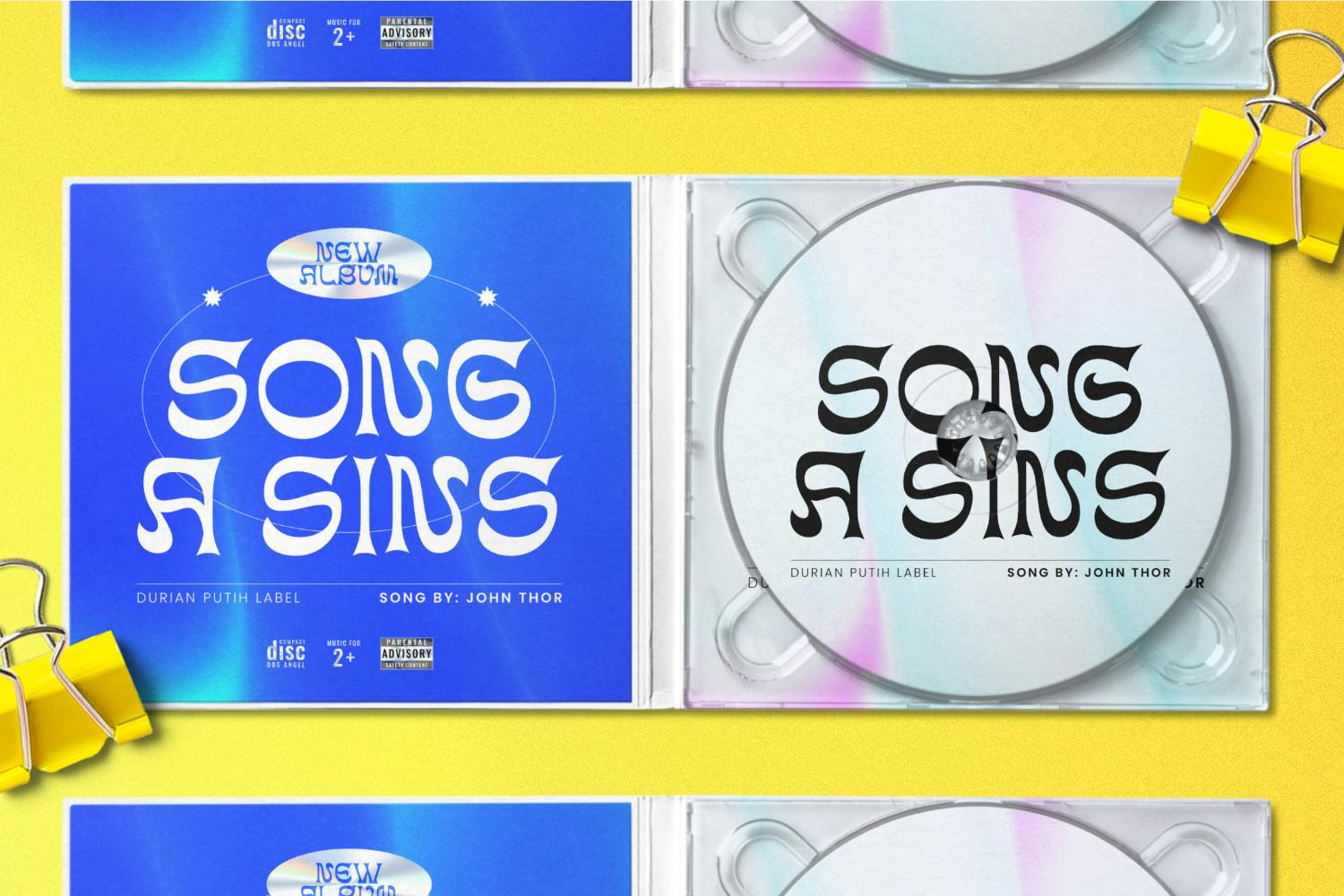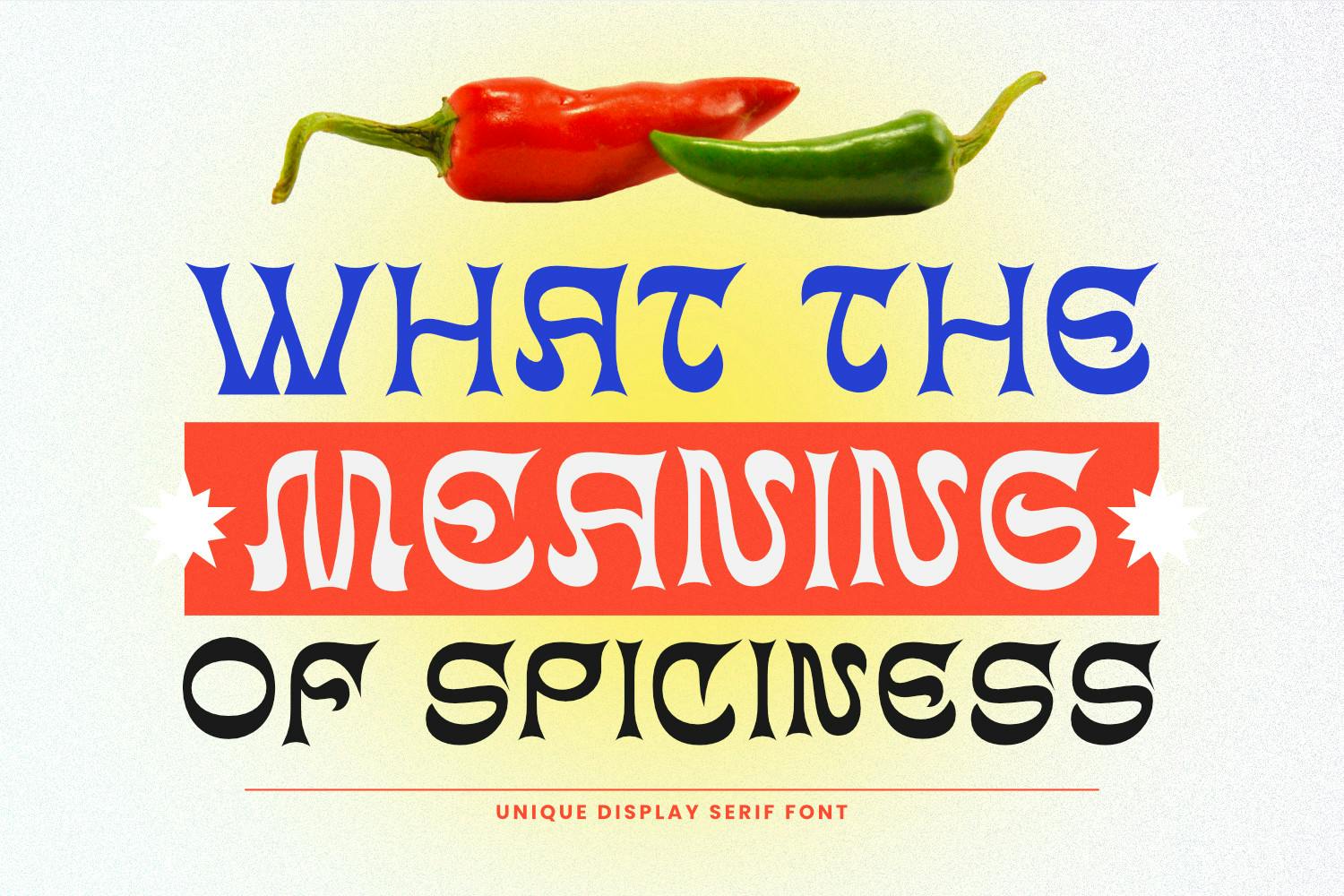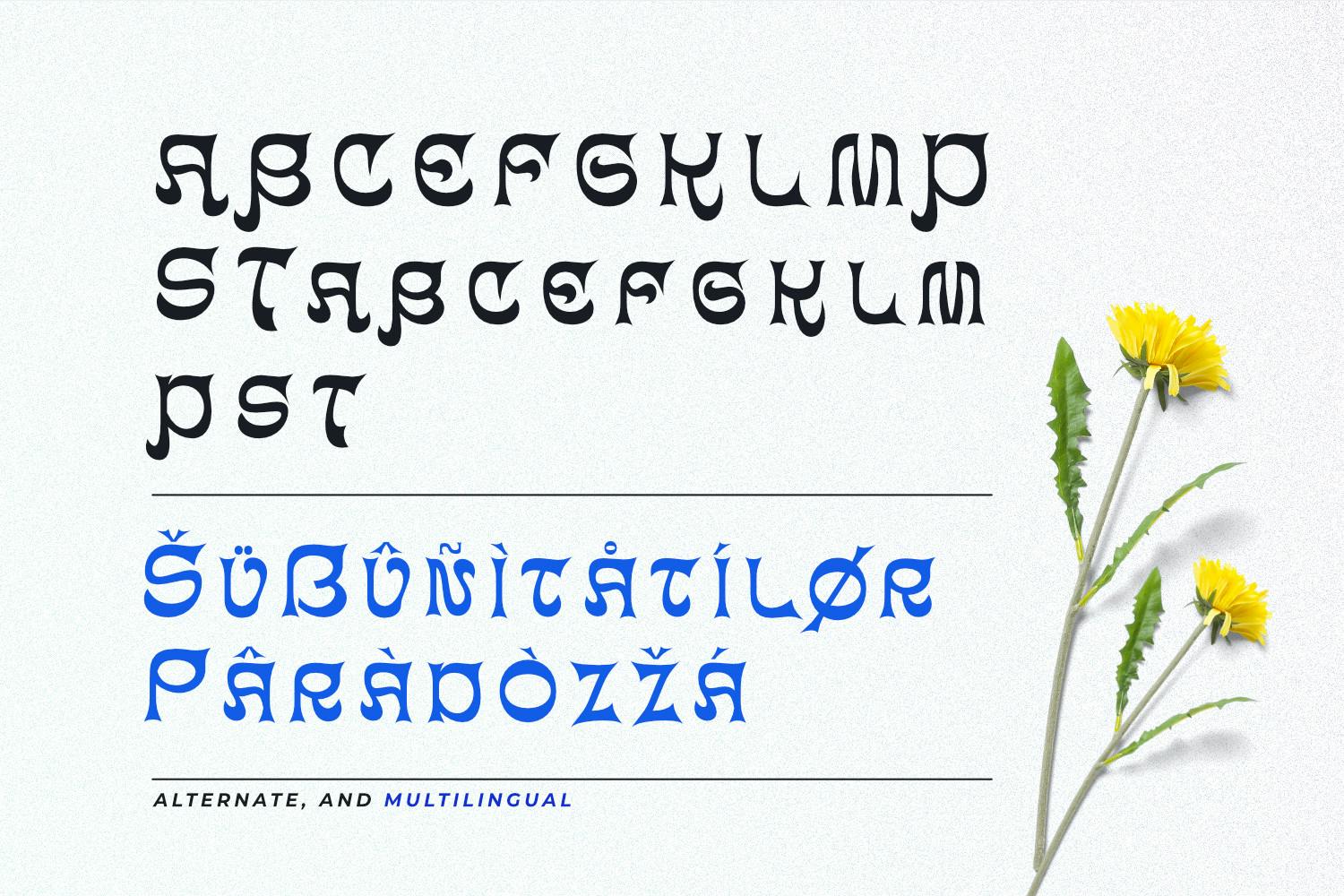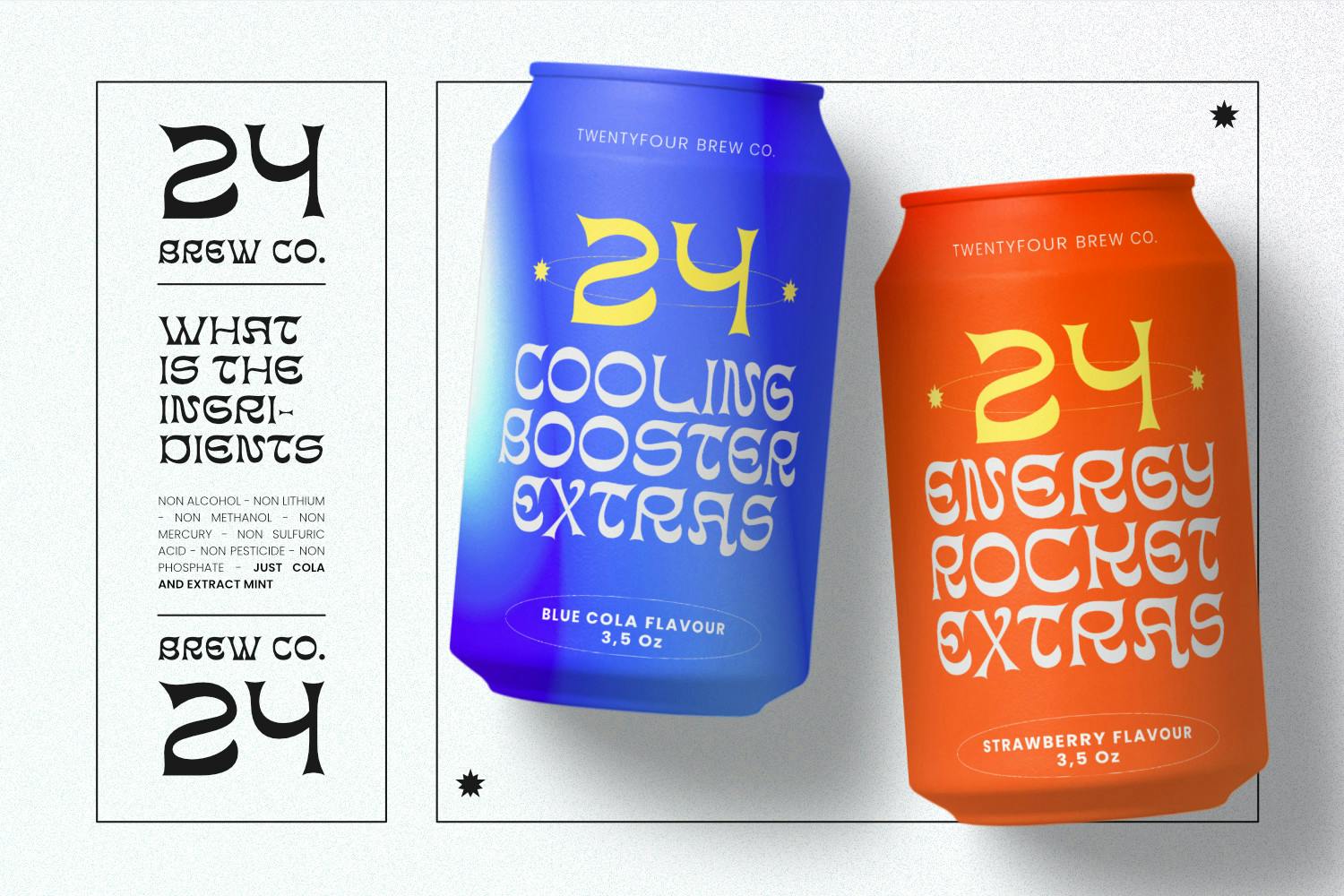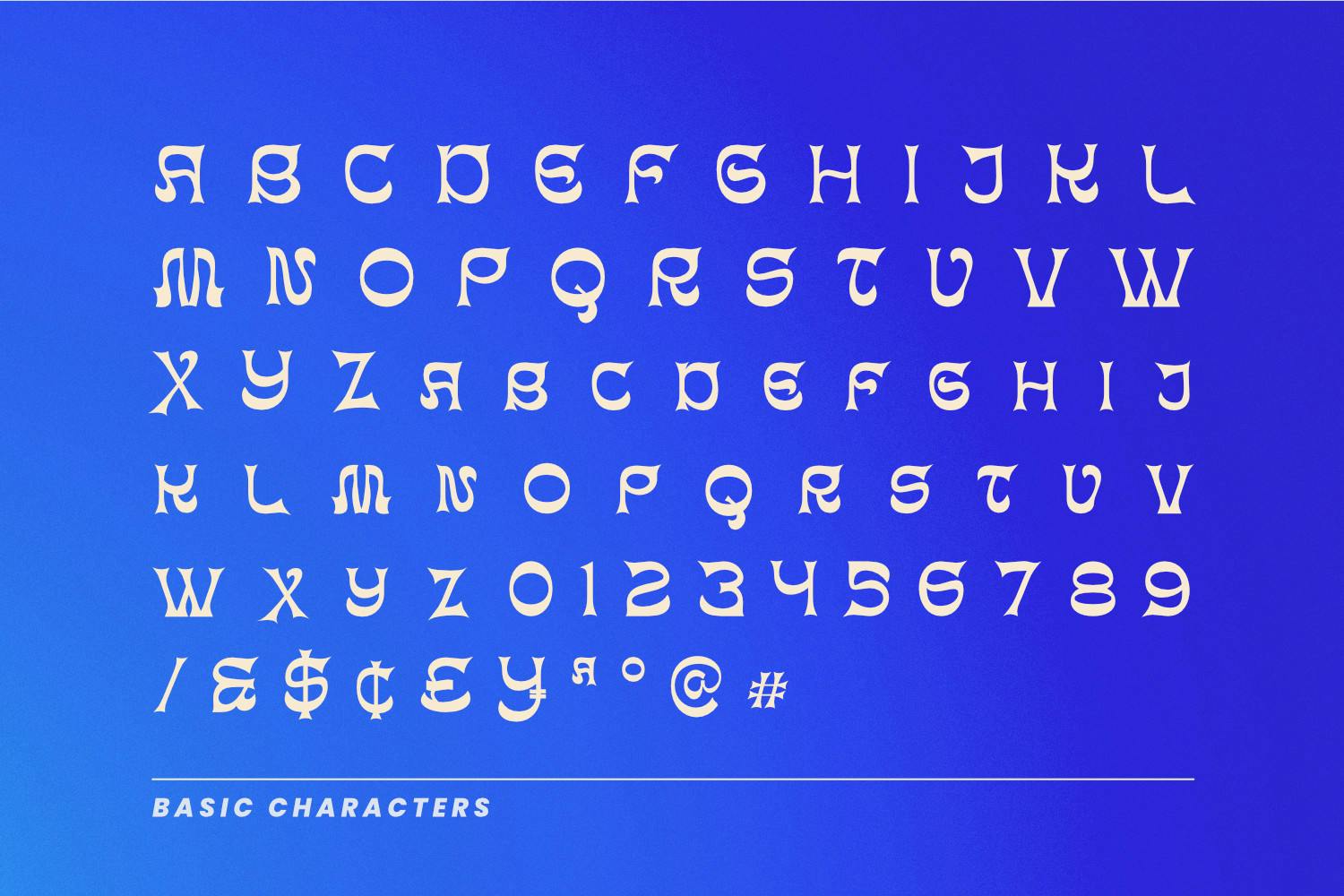
فونت Bonstar برای بسیاری از پروژههای شما از جمله لوگو و برندینگ، عکاسی، دعوتنامهها، واترمارکها، تبلیغات، طراحی محصولات، لوازمالتحریر، طراحیهای عروسی، برچسبها، بستهبندی محصولات، رویدادهای ویژه و بسیاری موارد دیگر مناسب است.